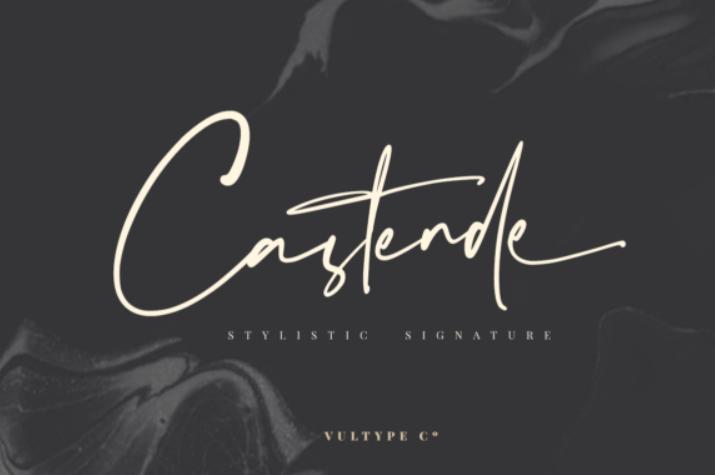
Castende - красивый и тонкий шрифт, излучающий элегантность и класс. Этот шрифт был специально разработан для тех, кому нужен красивый и освежающий вид своего дизайна. Castende имеет кодировку PUA, что означает, что вы можете легко получить доступ ко всем глифам.